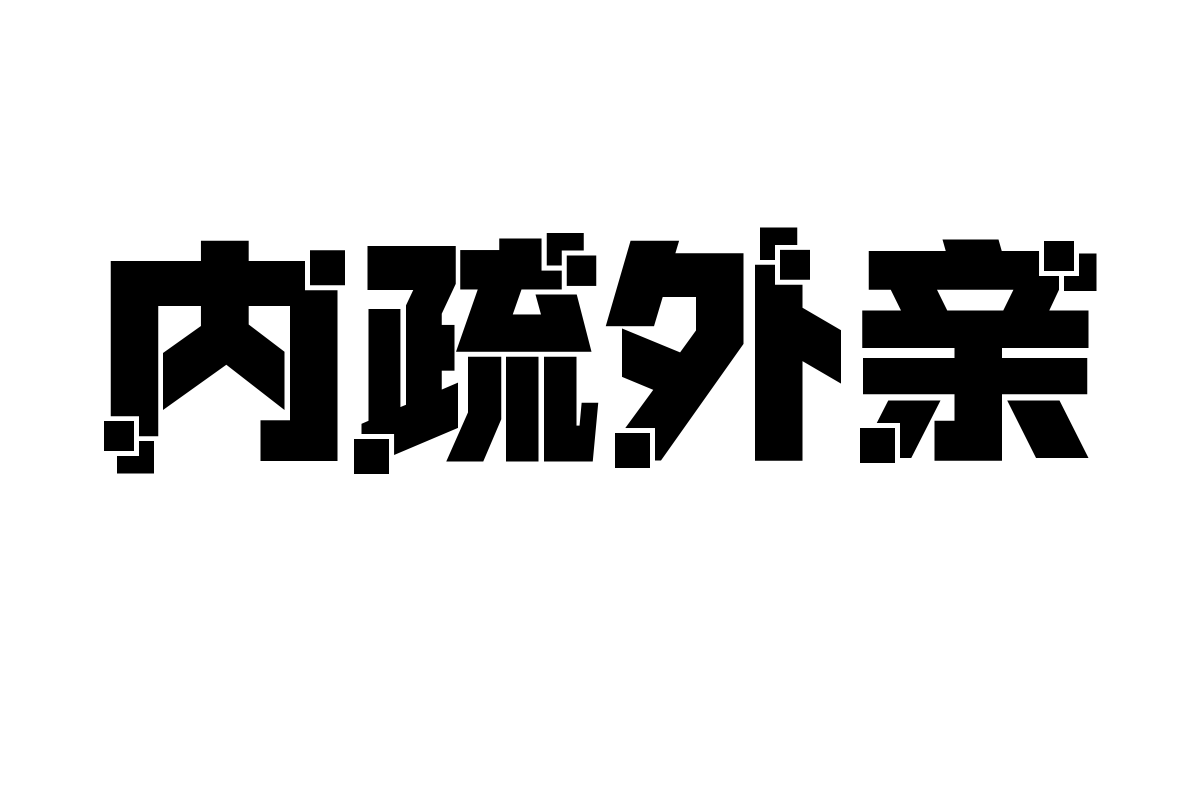
锐字太空跑酷像素字体是一款专为游戏设计,具有独特风格的字体。它采用了简洁的线条和几何形状,给人一种强烈的视觉冲击力。这种字体非常适合用于游戏界面、广告宣传等需要突出视觉效果的场景。
锐字太空跑酷像素字体的特点在于其独特的风格和易读性。它的笔画简洁明了,每个字母都经过精心设计,使其在屏幕上呈现出流畅而有力的视觉效果。同时,由于其简洁的线条和几何形状,使得整个字体看起来非常现代和时尚。
此外,锐字太空跑酷像素字体还具有很高的可定制性。设计师可以根据需要调整每个字母的大小、间距和颜色,以适应不同的应用场景和设计风格。这使得这款字体成为了一种非常灵活和实用的设计工具。
总的来说,锐字太空跑酷像素字体是一款非常适合游戏和广告领域的字体,它以其独特的风格和易读性,为设计师提供了更多的创作空间和可能性。